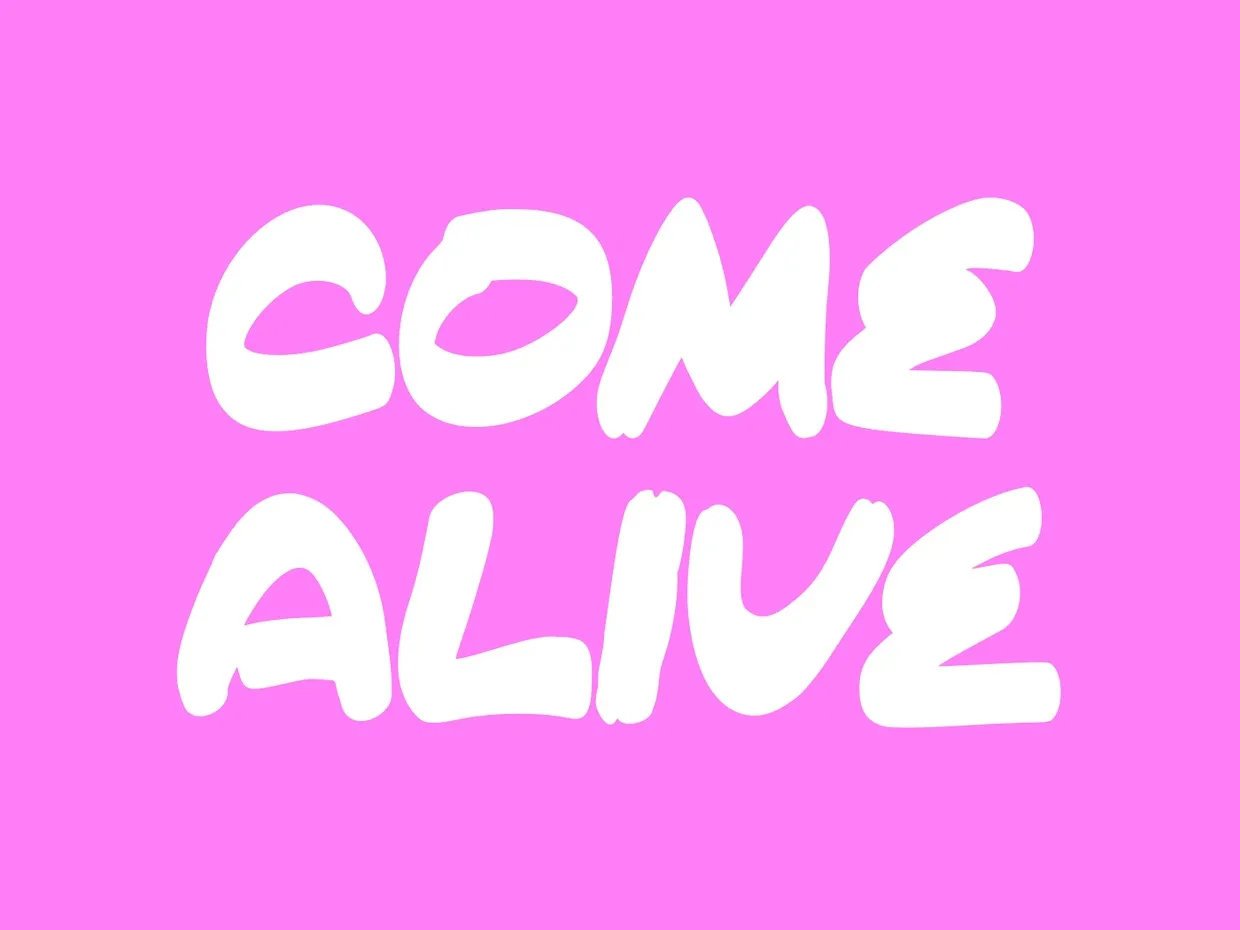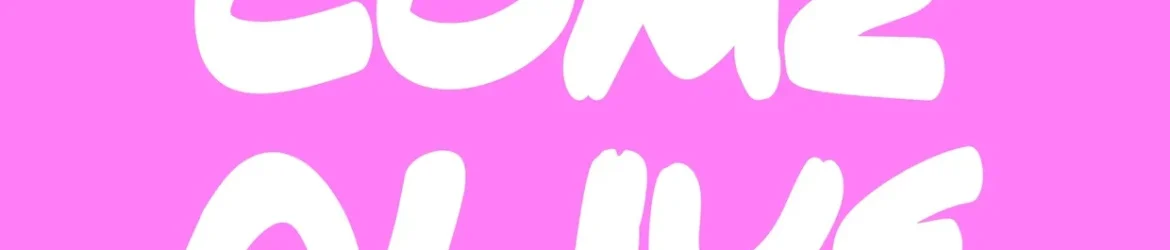
Introduzimos a fonte Come Alive Font! Este é um tipo de letras altamente emocional que irá adicioná-lo um toque genuíno e vivencial às suas criações. Através do design cuidadoso e compartilhamento gratuito pela No Regular Fonts, o Come Alive será uma adição indispensável em seu arsenal gráfico. Ideal para vários usos nas áreas da arquitetura de interiores, design gráfico, identidades visuais, logotipos, interfaces, infográficos, apresentações e eventos, a fonte Come Alive também é perfeitamente adequada para o ambiente do café, lojas de flor, mercados, publicidade, design gráfico e muito mais. O designer Hamilton criou um tipo único que convida ao experimentar experiências visuais vivas e reais em suas criações. Com a fonte Come Alive em seu arsenal, você pode transmitir sua mensagem com um toque especial, tornando cada projeto uma experiência emocional única para seus usuários.